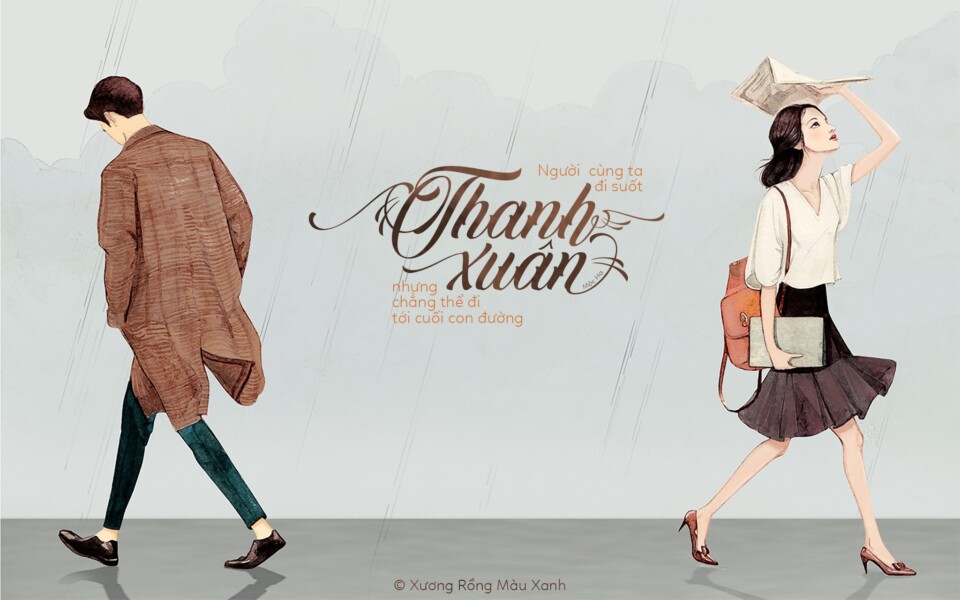
Khám Phá Vẻ Đẹp Tinh Tế Của Font Việt hóa MTD Familia Script – Tải Miễn Phí
Trong thế giới thiết kế đồ họa và in ấn, việc lựa chọn một Font Chữ phù hợp có thể tạo nên sự khác biệt lớn cho tác phẩm. Đặc biệt đối với học sinh, sinh viên khi chuẩn bị các dự án lớn, luận văn tốt nghiệp hay thiệp mời sự kiện, một phông chữ đẹp và dễ đọc là cực kỳ quan trọng. Hôm nay, chúng ta sẽ đi sâu vào khám phá sự quyến rũ của Font Việt hóa MTD Familia Script, một lựa chọn tuyệt vời dành cho những ai yêu thích phong cách viết tay bay bổng, nghệ thuật. Phiên bản Việt hóa này đảm bảo rằng bạn có thể sử dụng đầy đủ các ký tự tiếng Việt mà không gặp bất kỳ lỗi font nào.
Giới Thiệu Chi Tiết Về Font Việt hóa MTD Familia Script
MTD Familia Script là một font chữ script (kiểu viết tay) được thiết kế với sự mềm mại, uyển chuyển, mô phỏng nét chữ thư pháp hiện đại. Phiên bản gốc đã đẹp, nhưng nhờ có sự “Việt hóa” chuyên nghiệp, font chữ này đã trở nên hoàn hảo cho cộng đồng thiết kế Việt Nam. Sự Việt hóa này không chỉ đơn thuần là thêm dấu tiếng Việt mà còn chỉnh sửa các kerning (khoảng cách giữa các chữ) và ligatures (nối chữ) để đảm bảo văn bản tiếng Việt trông tự nhiên và hài hòa nhất. Đây là một yếu tố quan trọng, thường được tìm kiếm cùng với các font chữ miễn phí chất lượng cao và các tài liệu phục vụ cho các bạn học sinh, sinh viên.
Đối với các bạn học sinh, sinh viên, việc sử dụng các font chữ script như MTD Familia Script trong các dự án sáng tạo như làm bìa sách, poster, hay thiệp chúc mừng, sẽ giúp bài làm của bạn nổi bật hơn hẳn. Font này mang lại cảm giác cá nhân, ấm áp và rất sang trọng, phù hợp với các chủ đề về tình bạn, kỷ niệm, hoặc lễ tốt nghiệp. Nó là lựa chọn lý tưởng cho các ấn phẩm mang tính chất kỷ niệm cá nhân hoặc trường học.
Điểm Mạnh Vượt Trội Của Font Script Việt Hóa Này
Điều gì khiến MTD Familia Script trở thành một “must-have” trong bộ sưu tập font của bạn? Trước hết, đó là tính thẩm mỹ cao. Font có các đường nét thanh thoát, rõ ràng, dù là font script nhưng vẫn giữ được độ dễ đọc cần thiết. Sự kết hợp tinh tế giữa nét dày và nét mỏng tạo nên chiều sâu và sự tinh tế hiếm thấy trong các font chữ viết tay miễn phí khác. Đặc biệt, nó được tối ưu hóa để hiển thị đẹp mắt trên cả các tài liệu in ấn và màn hình kỹ thuật số.
Sử Dụng Font MTD Familia Script Trong Các Dự Án Giáo Dục
Khi chuẩn bị tài liệu cho kỳ thi tốt nghiệp hoặc các buổi thuyết trình quan trọng, nhiều học sinh muốn tạo ấn tượng chuyên nghiệp nhưng vẫn mang đậm dấu ấn cá nhân. Font MTD Familia Script rất thích hợp để làm tiêu đề cho các slide PowerPoint (chú ý không dùng cho phần nội dung chính), thiết kế bìa tiểu luận, hoặc làm chữ ký số cho các văn bản cá nhân. Nó thể hiện sự đầu tư và sáng tạo của người dùng. Việc tối ưu hóa cho tiếng Việt là lợi thế lớn nhất, giúp loại bỏ nỗi lo về các lỗi font phổ biến khi sử dụng các font nước ngoài, đảm bảo sự liền mạch trong quá trình thiết kế các ấn phẩm học tập.
- Tính ứng dụng cao: Phù hợp với nhiều mục đích, từ thiệp cưới, logo cá nhân, đến các ấn phẩm liên quan đến trường học và dự án cuối cấp.
- Tối ưu hóa tiếng Việt: Hỗ trợ đầy đủ các dấu và ký tự đặc biệt, đảm bảo tính nhất quán và chuyên nghiệp của văn bản.
- Cảm xúc: Truyền tải được sự lãng mạn, thanh lịch và cá tính mạnh mẽ, rất phù hợp với các thiết kế mang tính kỷ niệm.
Tóm lại, Font Việt hóa MTD Familia Script là một tài sản vô giá trong thư viện font của bất kỳ nhà thiết kế nào, từ chuyên nghiệp đến các bạn học sinh, sinh viên đang theo đuổi đam mê sáng tạo. Vẻ đẹp tinh tế, sự hỗ trợ tiếng Việt hoàn hảo, và tính ứng dụng đa dạng khiến font này trở thành lựa chọn hàng đầu cho các dự án cần sự bay bổng, nghệ thuật, đặc biệt là trong các khâu thiết kế quan trọng. Đừng ngần ngại tìm kiếm và tải về ngay hôm nay để làm phong phú thêm kho tàng Font Chữ của mình. Chúc các bạn thành công trong việc tạo ra những tác phẩm thiết kế độc đáo, ấn tượng, đặc biệt là trong các sự kiện quan trọng như lễ tốt nghiệp hay các kỳ thi cuối cấp.